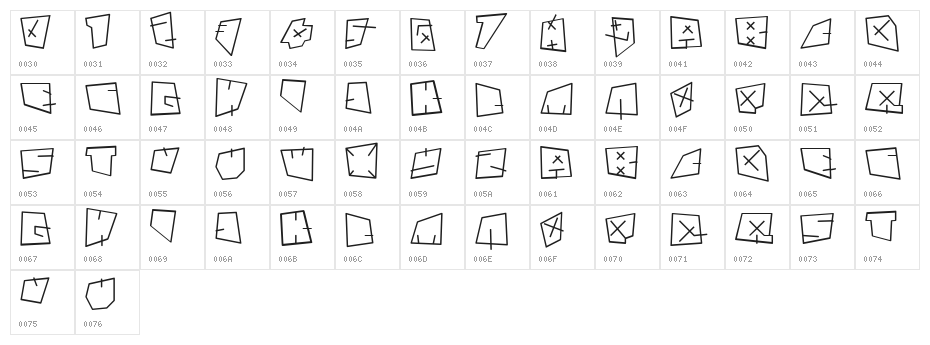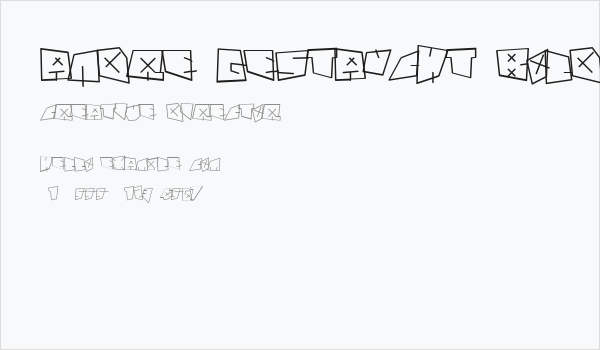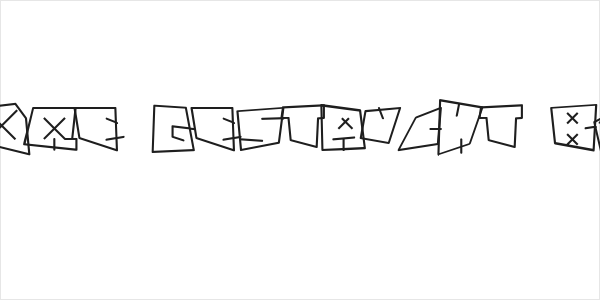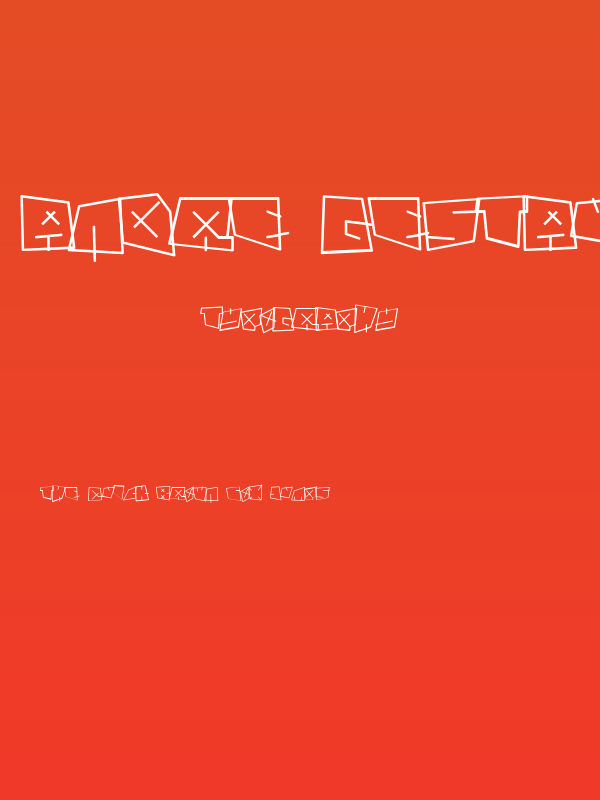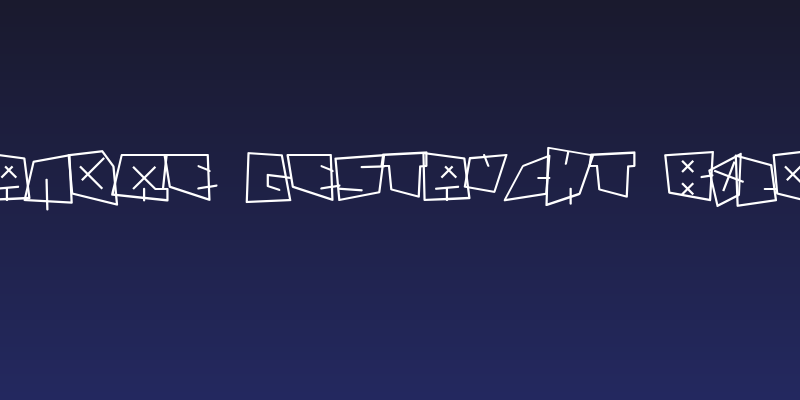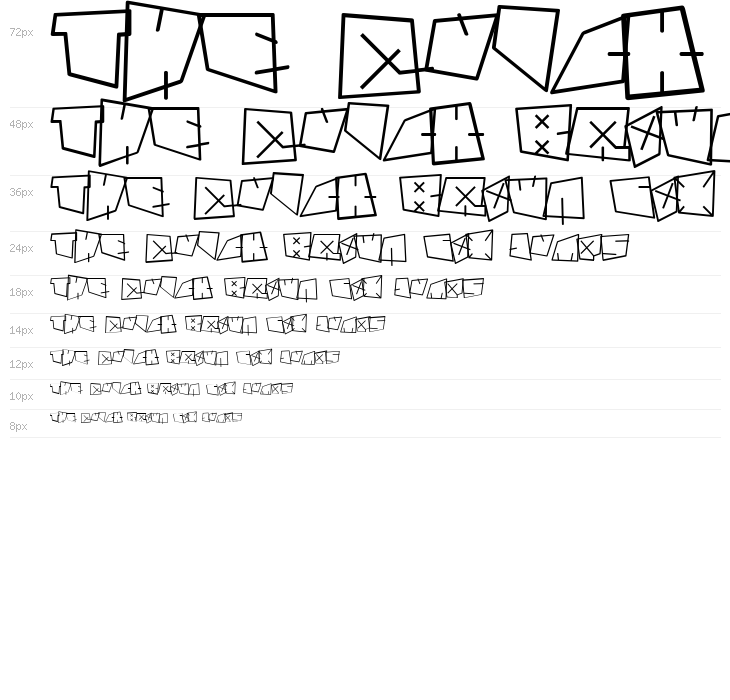
andre gestaucht bold Font
✎ Graffiti
| Categorii | Graffiti |
| Stil general | Modern, Decorative |
| Caz de utilizare | Logos, Posters, Artistic projects |
| Proiecte propuse | Ideal for street art-inspired designs, edgy posters, album covers, and creative branding projects. |